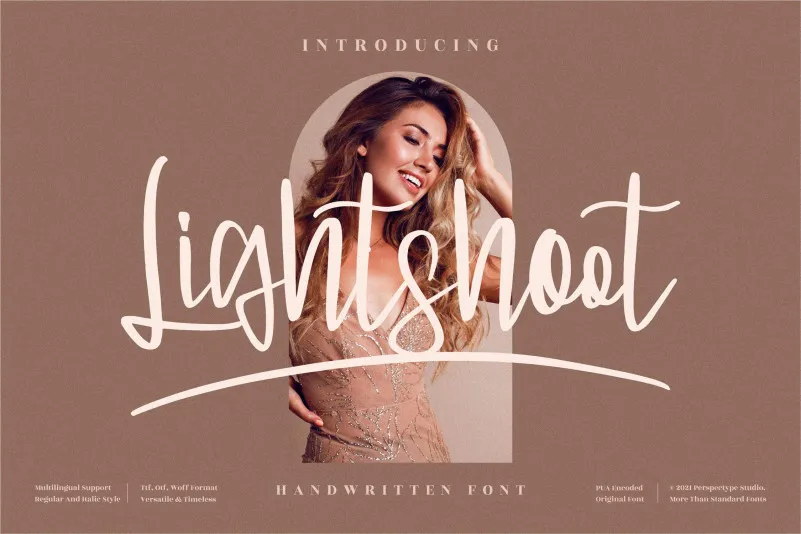
Lightshoot Font – Fonte Grátis
Lightshoot Font
Esta é uma linda e eterna fonte escrita à mão. Seu designer, perspectype, criou um estilo que se destaca entre as demais, oferecendo a cada letra um toque único e encantador. Esta fonte perfeita para criar logos memoráveis, marcas impactantes e frases inspiradoras que chamam atenção. A sua beleza é notável em cada caractere, fazendo com que suas criações despertem vida e atração imediatas. Para quem busca uma fonte que se destaca no design de marca, esta é a escolha certa. Perspectype trouxe um conjunto de detalhes meticulosos e sutis para criar uma experiência visual envolvente, tornando cada frase e logo mais interessante e memorável. Com essa fonte em seu arsenal, qualquer projeto que você desenvolver terá uma riqueza visual sem igual.